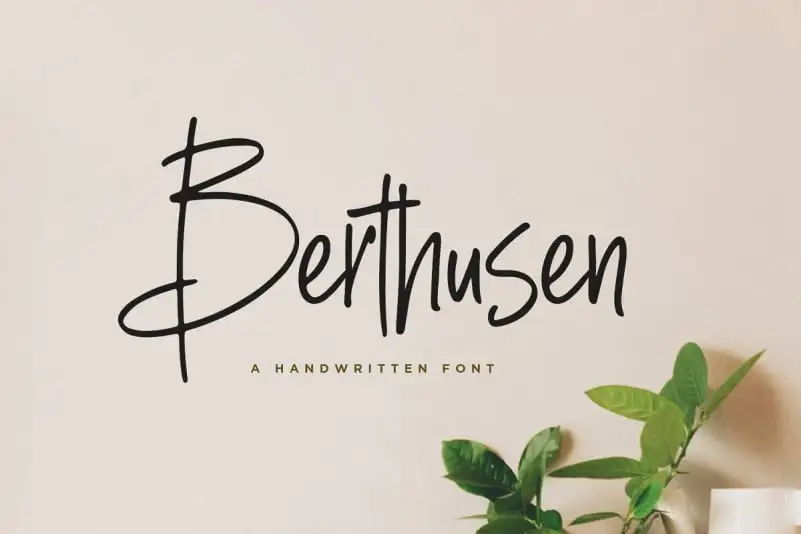
Berthusen Handwritten Font – Fonte Grátis
Berthusen Handwritten Font
Essa é uma fonte Script que chama Berthusen Handwritten Font, projetada pela designer 1001fonts. Esta fonte tem um estilo retrô e escrita manual, com linhas variadas para transmitir elegância e estilo. Sabrcreative concebeu este design pensando em seu uso para uma variedade de projetos, desde logotipos e identidades corporativas até cartões de convite, embalagens, cartazes ou etiquetas. Berthusen Handwritten é perfeitamente adequado para vários usos criativos. Suas linhas fluidas e limpas se destacam em projetos como invitations, designs de estação (stationery), decorações de casamento, posts nas redes sociais, anúncios, embalagens dos produtos, fotografias, marcas ou watermark, eventos especiais, citações, moda e muito mais. Este design suave e feminino será um excelente complemento para seu próximo projeto visual.